ТОП 30 шрифтов с засечками в 2020 году Ⓐ Shriftkrasivo.ru
Шрифты с засечками можно использовать для самых разных целей — от общего основного текста до заголовков, для отображения копий. Это типографский вариант, который широко используется для цифровых и печатных целей, и такие устройства, как Amazon Kindle, даже используют шрифт с засечками в качестве шрифта по умолчанию.
Эти потрясающие шрифты с засечками вы можете использовать для своего следующего дизайн-проекта. Они смелые, красивые и несут много влияния. Все включенные пакеты шрифтов состоят из разных вариантов, которые дают вам много возможностей для экспериментов в ваших проектах.
Bw Glenn Slab
Bw Glenn — это семейство шрифтов с засечками, имеющими современный и профессиональный дизайн, что делает его подходящим выбором для всех видов бизнеса, креатива и брендинга. Шрифт поставляется в 8-ми различных видах, начиная от тонкой линии, как волосок до черного жирного.
Calvin
Calvin — это стильный шрифт с засечками, имеющий современный дизайн. Этот шрифт идеально подходит для всех видов творческого и профессионального дизайна, от логотипов до постеров и многого другого. Шрифт доступен в 8 различных весах.
Yahya
Элегантное семейство шрифтов slab serif с 5 различными шрифтами. Вы можете использовать этот шрифт для разработки логотипов, этикеток, визиток и многого другого для брендов стиля жизни и моды. Шрифт включает как прописные, так и строчные буквы.
Boxing
Этот смелый шрифт с засечками отличается смелым ретро-дизайном и набором заглавных букв. Он наиболее подходит для создания заголовков и заголовков для различных проектов, связанных с развлечениями. Включает многоязычную поддержку.
Dezire
Dezire — это шрифт с засечками с современным дизайном.
Этот шрифт идеально подходит для всех видов спортивного дизайна, а также для создания больших смелых заголовков для постеров и заголовков веб-сайтов.
Kula
Kula — это элегантный и современный шрифт с засечками, имеющий толстый и смелый дизайн. Этот шрифт идеально подходит для создания заголовков, заголовков плакатов и даже логотипов. Шрифт включает 4 стиля: жирный, контурный, теневой и размытый.
Galvin
Galvin — это полное семейство шрифтов slab serif с 8 различными значениями веса: от обычного, контурного, тонкого и жирного. Сжатый дизайн шрифта делает его отличным выбором для создания поздравительных открыток, плакатов, логотипов и наклеек.
Controwell
Controwell — это элегантный шрифт с засечками, дизайн которого навеян викторианской эпохой. По словам создателя, шрифт состоит из двух слоев, которые придают ему металлический вид.
Neue Stanley
Neue Stanley — это современный винтажный шрифт, разработанный по мотивам винтажных вывесок, плакатов и баннеров.
Xantheus
Xantheus — это жирный шрифт с засечками, который можно использовать для создания заголовков и заголовков для плакатов, заголовков веб-сайтов и баннеров. Шрифт поставляется в двух весах, обычный и округлый.
Atletico
Atletico — это современный бесплатный шрифт с засечками, имеющий 6 различных весов. Он включает как заглавные, так и строчные буквы. Бесплатная версия шрифта разрешена только для личных проектов.
Fable Bug
Fable Bug поставляется с забавным и причудливым дизайном, который делает его идеальным для создания обложек книг, плакатов и поздравительных открыток, особенно связанных с детьми. Шрифт включает в себя все символы, цифры и символы.
Blade
Blade — это шрифт с засечками в стиле ужасов с уникальным дизайном, который больше всего подходит для постеров фильмов на тему ужасов, обложек книг, поздравительных открыток и баннеров.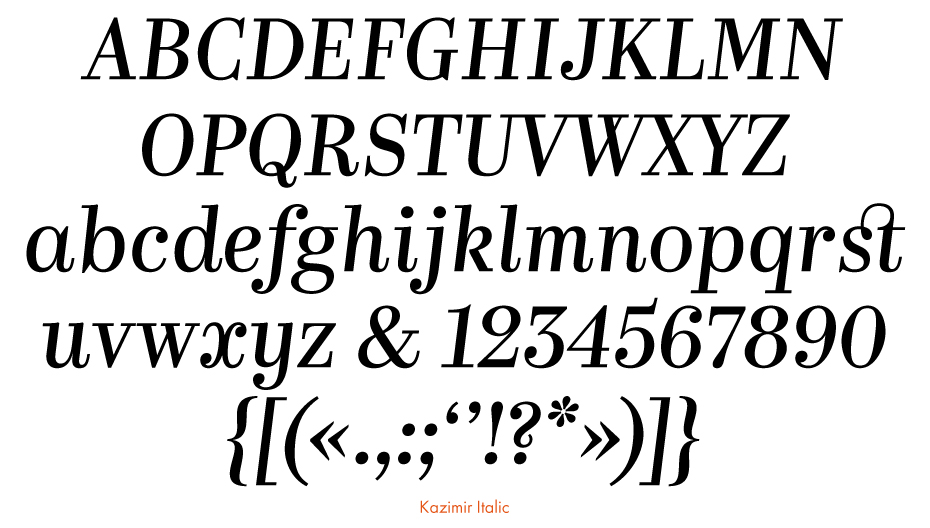
Ropstone
Ropstone — это винтажный шрифт с засечками, выполненный в двух стилях: винтажные бордюры и орнаменты. Этот шрифт идеально подходит для создания значков, логотипов, плакатов и наклеек.
Ace Serif
Ace Serif — это современный шрифт slab serif с профессиональным дизайном, что делает его отличным выбором для разработки современных заголовков веб-сайтов, плакатов, заголовков, логотипов и многого другого. Шрифт приходит к вам в 8 различных весах.
Gosha Sans
Другой бесплатный и стильный шрифт slab, который вы можете использовать для создания привлекательных заголовков и заголовков для плакатов, сайтов, баннеров и многого другого. Этот шрифт оформлен в стиле русских дизайнеров.
Brewski
Brewski — это нарисованный вручную шрифт с засечками в винтажном стиле, созданный для создания дизайна для пивоваренного бизнеса, но вы также можете использовать его для создания других видов креативных значков и постеров.
Murmers
Шрифт Murmers slab serif представлен напряженным дизайном, что делает его больше похожим на название из старинного фильма. В дополнение к шрифту, он также включает в себя бонусный векторный файл AI, который вы можете использовать со своими собственными проектами.
VIDIZ PRO
Vidiz Pro — это элегантный шрифт с засечками, имеющий роскошный дизайн. Это делает его идеальным выбором для разработки логотипа, плаката, заголовка веб-сайта и дизайна полиграфических проектов, связанных с модными и роскошными брендами. Шрифт также поставляется в нескольких разных стилях.
Univia ProВыберите шрифт с индивидуальностью, как этот, разработанный Olivier Gourvat в декабре 2015 года. Благодаря плавным изгибам и более закругленным углам отлично подходит для проектов, которым требуется современный стиль.
Семейство шрифтов EslavaОтображаемый шрифт с геометрическим угловатым видом, это семейство шрифтов включает шесть стилей на выбор.